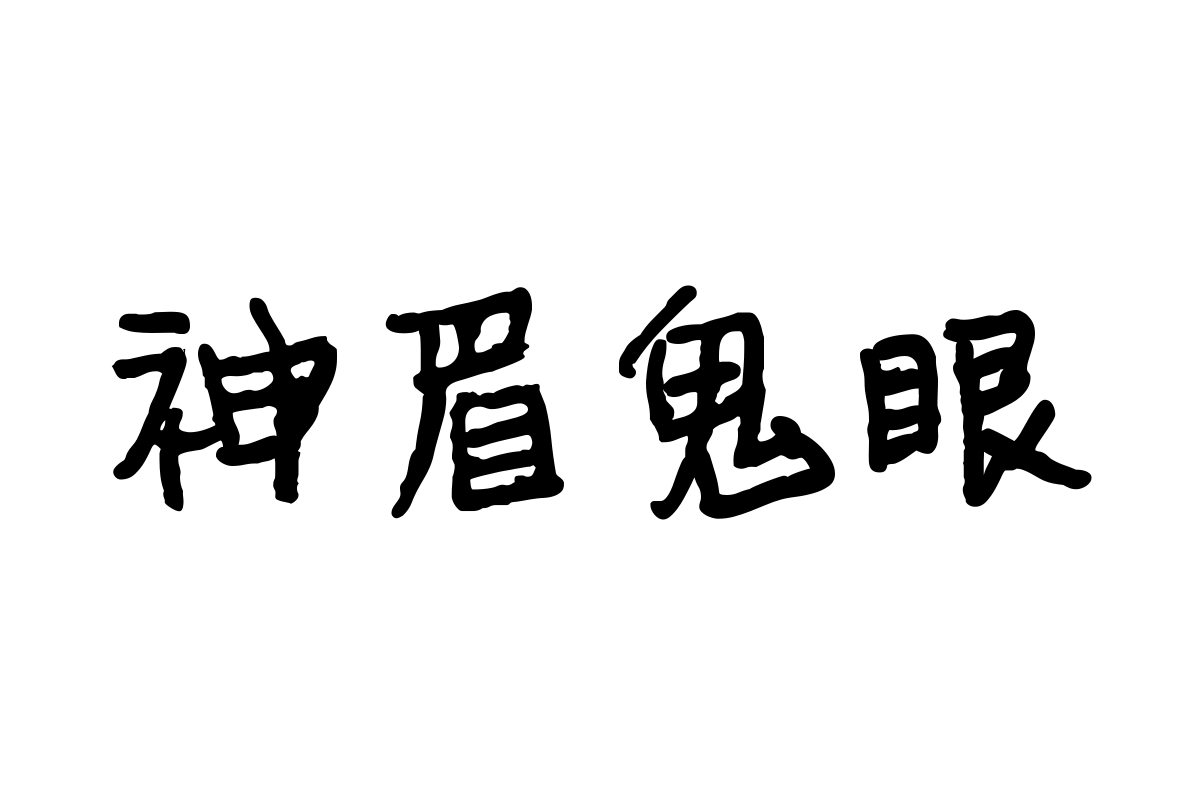
字体管家娜娜是一款专为中文用户设计的专业字体,具有以下特点:
1. 字形美观:字体管家娜娜采用了独特的字形设计,使得文本在视觉上更加美观,提高了阅读体验。
2. 可读性强:字体管家娜娜的字形结构清晰,笔画流畅,使得文本在阅读时更加容易理解,降低了学习成本。
3. 适用性广:字体管家娜娜适用于各种场合,无论是正式的商务文件、学术报告,还是日常的笔记记录,都能展现出其专业的气质。
5. 个性化定制:字体管家娜娜提供了丰富的个性化选项,用户可以根据自己的喜好进行字体风格的调整,打造出独一无二的个性文字。
总之,字体管家娜娜是一款集美观、易读、实用于一体的专业字体,适合各类中文用户的使用需求。